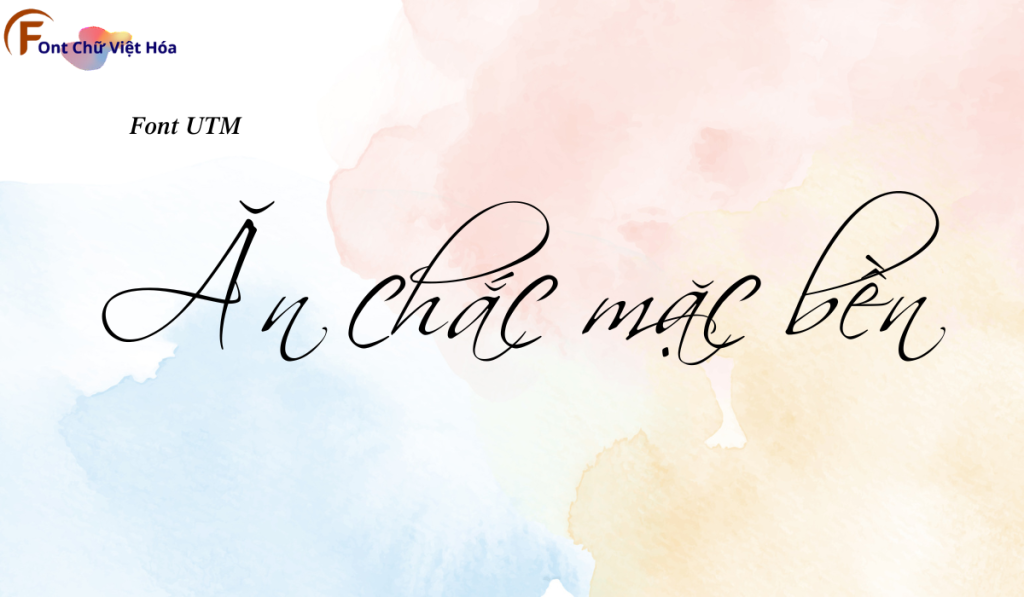
Font UTM Scriptina Kt Việt Hóa
Tác giả: UTM Scriptina Kt
Bộ Font: UTM
Kiểu chữ: Chữ thảo
Độ dày: Thường
Font UTM Scriptina Kt Việt Hóa là một font chữ thảo nghệ thuật, thuộc bộ font UTM. Được thiết kế với mục tiêu mang lại sự sáng tạo và độc đáo, font này lý tưởng cho các dự án thiết kế như logo, poster, và bao bì sản phẩm. Với các nét chữ mềm mại và độ dày đều đặn, Font UTM Scriptina Kt Việt Hóa không chỉ dễ đọc mà còn tạo cảm giác hiện đại và phá cách. Việc Việt hóa font giúp người dùng dễ dàng tích hợp vào các thiết kế tiếng Việt, mang lại sự tiện lợi và nâng cao tính thẩm mỹ.